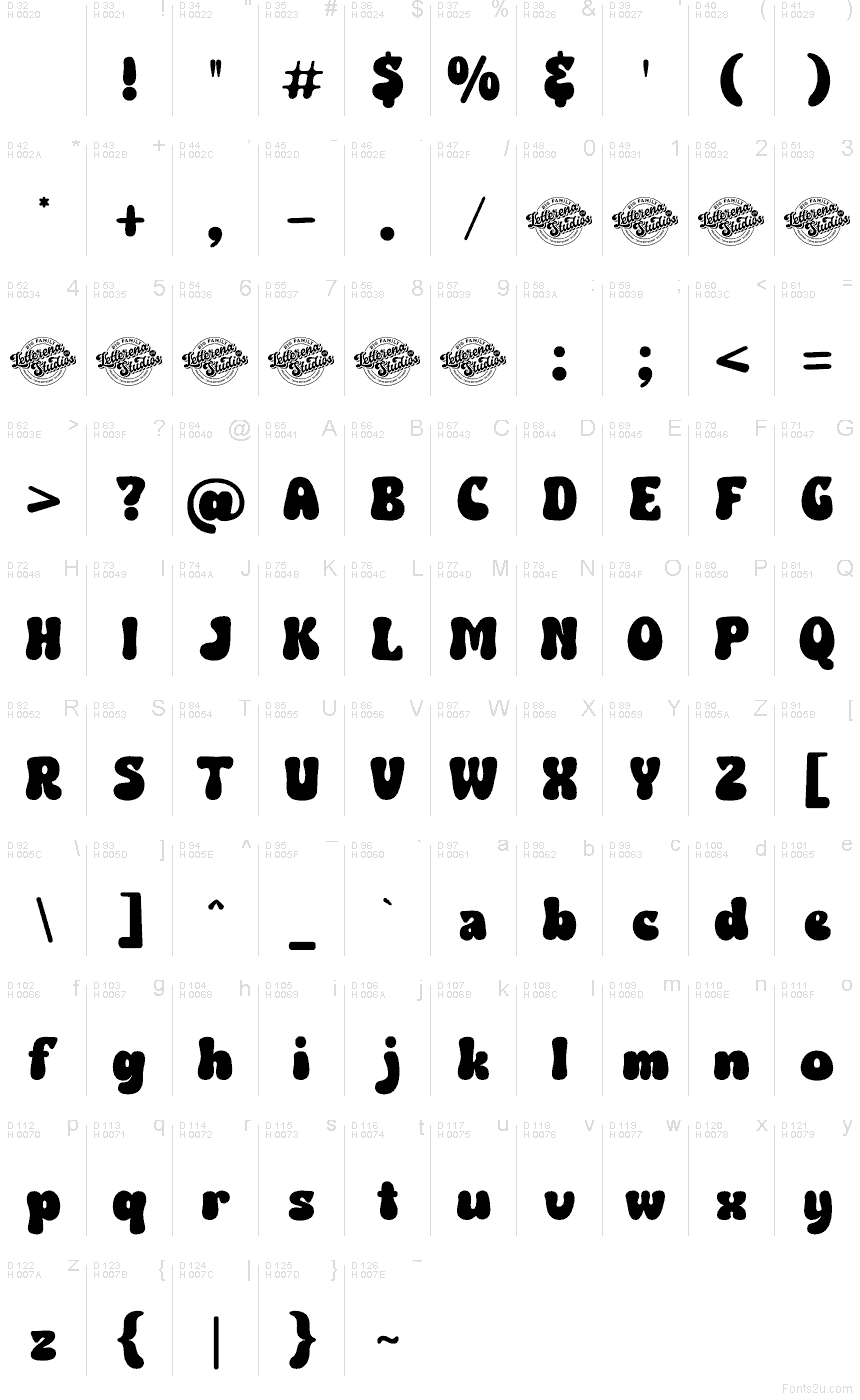
Histea Ballon od Letterena Studios je bezplatné kreslené display písmo v hravém retro stylu se širokými, nafouknutými literami a živou, nepravidelnou siluetou. Zaoblené rohy, zúžená napojení tahů a drobné vnitřní prostory propůjčují nápisům měkký, poddajný vzhled lité pryže nebo balónků.
Tyto zaoblené tvary připomínají hravé ilustrace známé z dětské zábavy a obalů sladkostí či pochutin. Hodí se také na hudební plakáty a neformální branding akcí. Tento styl působí obzvlášť přesvědčivě u mladého publika a u značek zaměřených na cukrovinky, hračky nebo popkulturu.